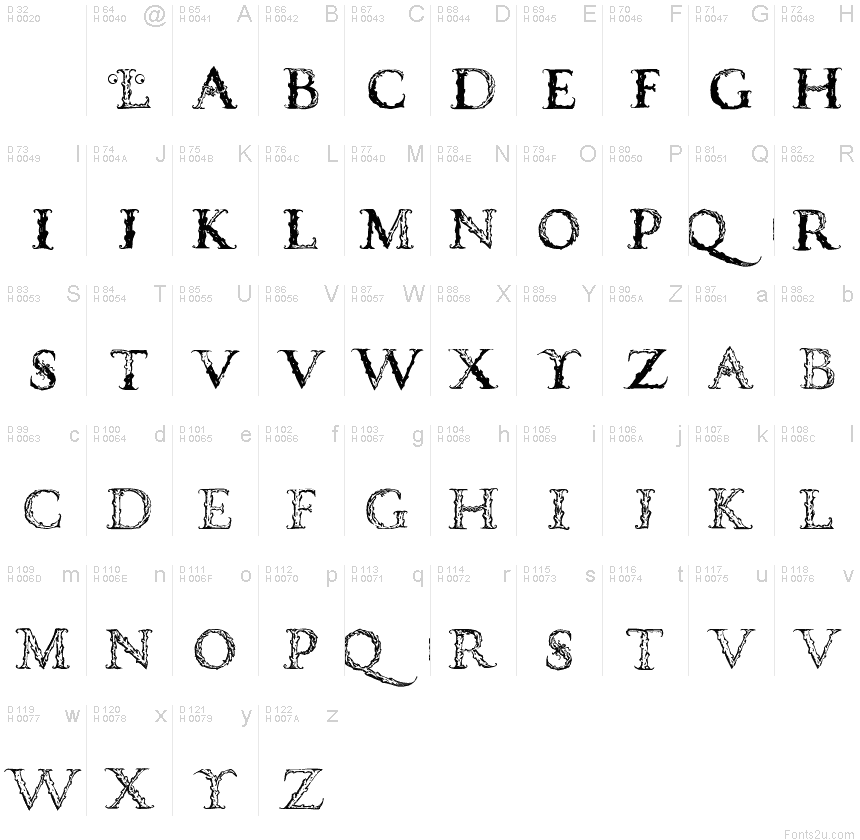
Vespasian Caps, odświeżony przez Manfreda Kleina, to darmowy font displayowy w stylu renesansowym, którego litery wyglądają, jakby zostały wyciosane w surowej korze i splątanych pnączach. Wielkie litery są jednocześnie antyczne i nieokiełznane – z kolczastymi krawędziami, zawiniętymi końcówkami i drobnymi botanicznymi akcentami, które nadają całości klimat starego drzeworytu.
Sprawdza się na okładkach książek, tytułach plakatów, grafikach historycznych, opakowaniach w stylu fantasy i teatralnych planszach tytułowych, gdzie darmowy krój z historycznym pazurem wypada znacznie lepiej niż zwykłe, równe liternictwo. Stosuj go do krótkich słów, inicjałów lub monogramów – gęsta faktura i pełne detali organiczne kształty robią świetną robotę.